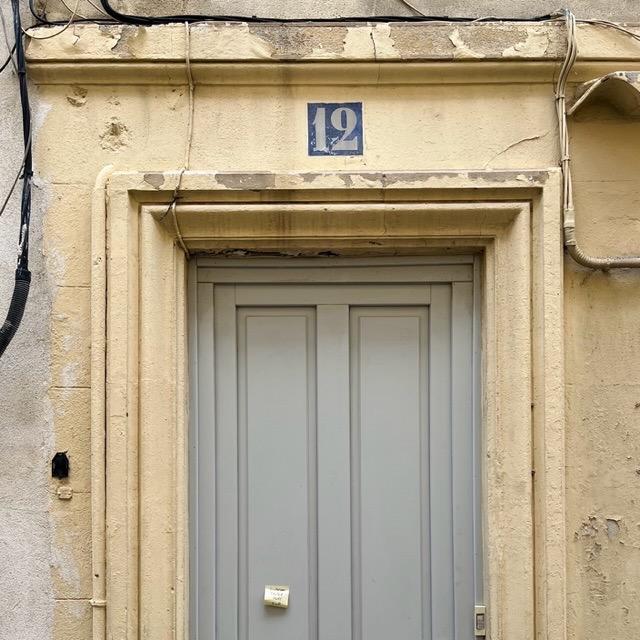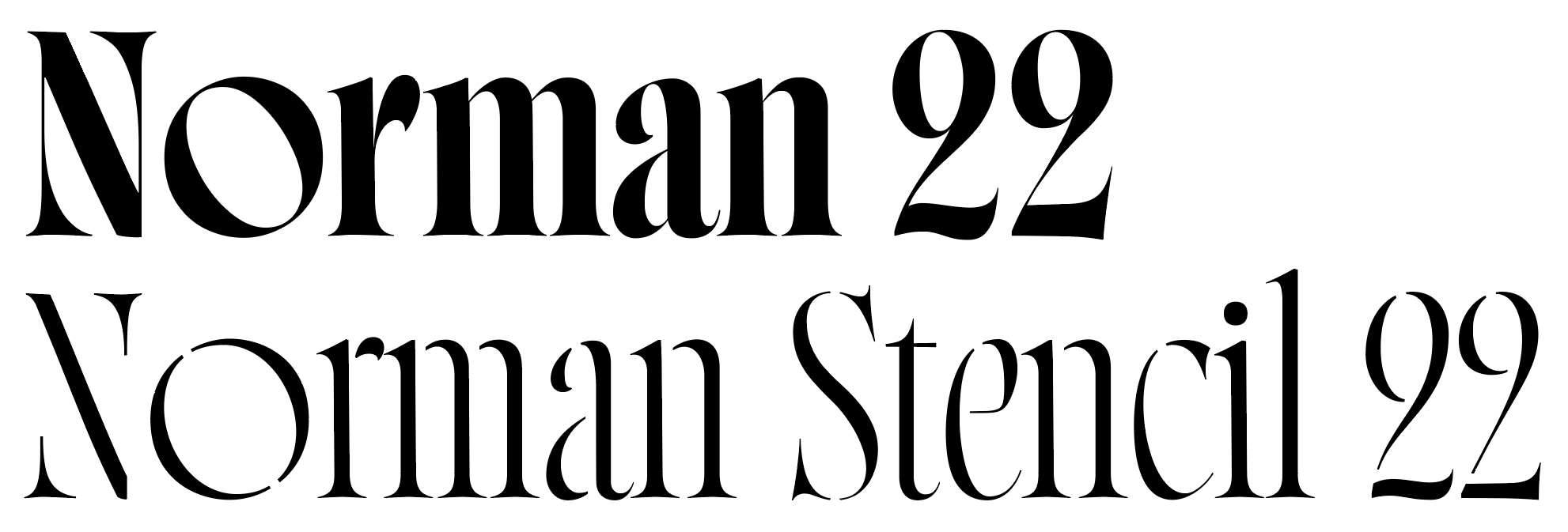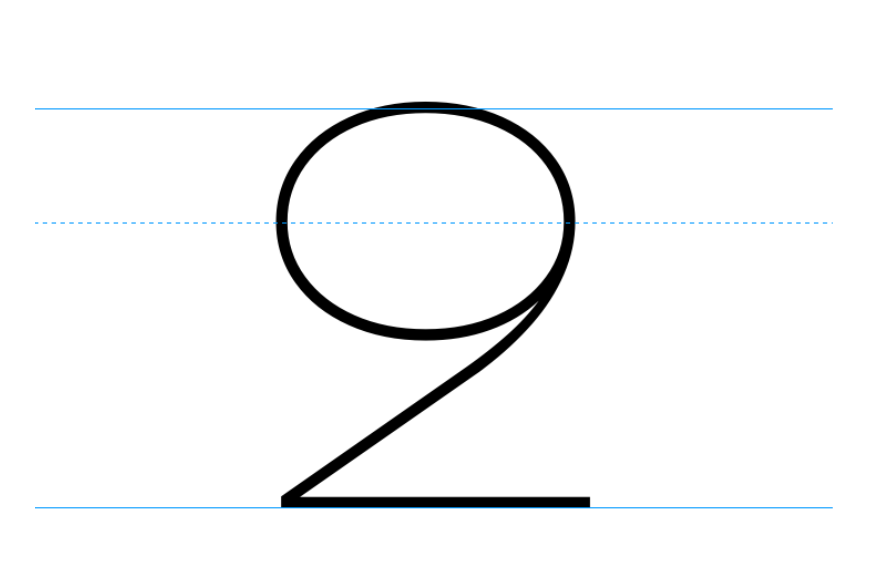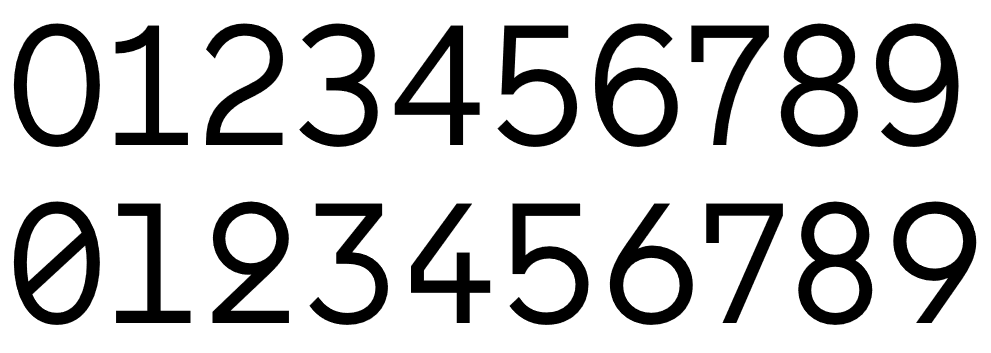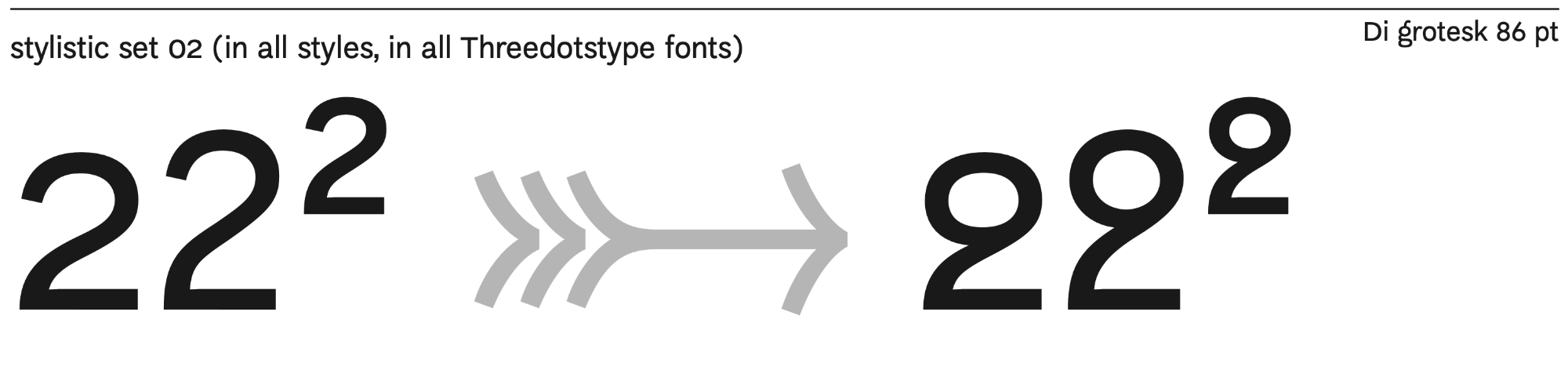
Schriften mit geschlossener Zwei (two with a loop)
Und dann wäre da noch die Frage nach dem Namen dieser Form. Hier mal ein paar Ansätze aus unterschiedlichen Richtungen:
- Two with a loop
- Schlaufen-Zwo
- geschlossene Zwei / closed two
- O₂
Geht es nur mir so, dass die Zwei mit Punze derart gehäuft irgendwie abstrakt wirkt, bzw. mein Gehirn sich gerade nicht zwischen 999 und 222 entscheiden kann?
Ein bisschen gewöhnungsbedürftig ist die Form sicherlich. Aber aus meiner Erfahrung geht das recht schnell. Ich hab vor einiger Zeit mal eine Studie mit dieser Form gestaltet und da hat sich von Kundenseite zumindest niemand beschwert ...
Ich sehe die Form eher als Experiment an. Und man findet sie ja auch häufig bei den „Hipster-Fonts“. Für sachliche, seriöse Texte oder wo Funktion an erster Stelle steht, würde ich sie nicht verwenden, ähnlich der Kategorie Schwungbuchstaben etc.
Wie weiter oben geschrieben hat Koch diese Form in vielen seiner Schriften verwendet. Die Form ist also schon etwas älter als die Hipster-Fonts und hat sicher auch eine Geschichte (Aber welche?). In einem Geschäftsbericht würde ich sie nicht unbedingt einsetzen aber bei normalen Texten finde ich das je nach Kontext und verwendeter Schrift durchaus legitim.
Hat sich aber eben bis heute nicht wirklich durchgesetzt und hat daher noch immer diese experimentelle Note. Das ist beim einfachen und komplexen a/g zum Beispiel etwas anderes.